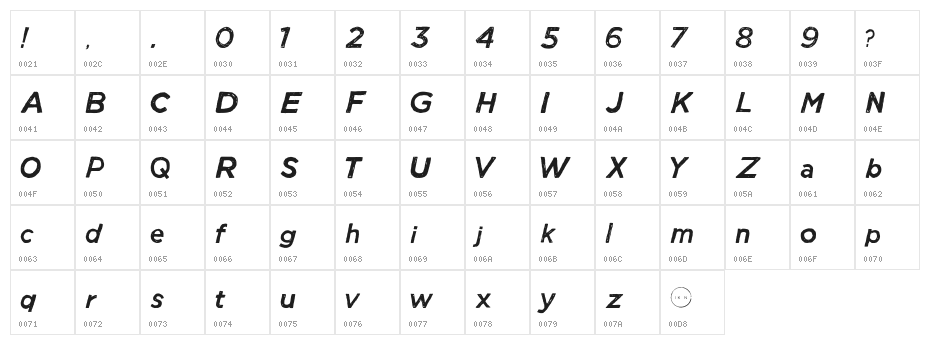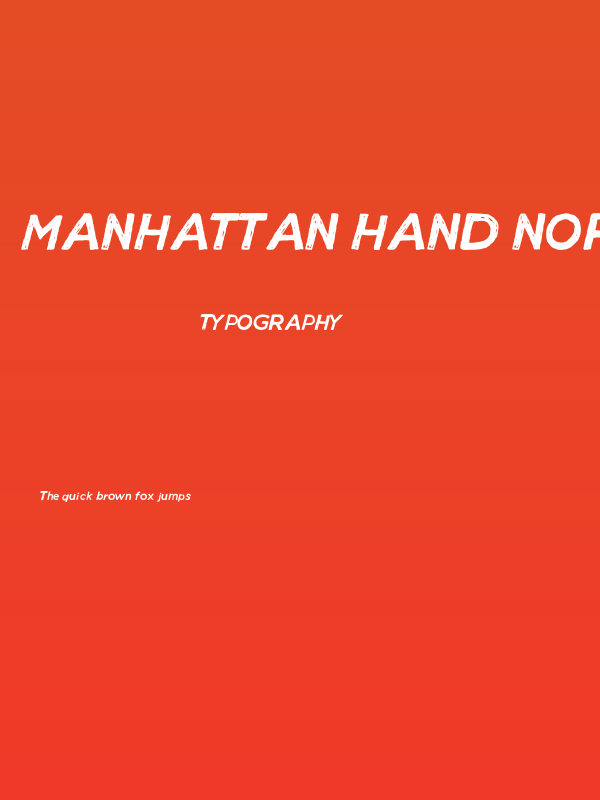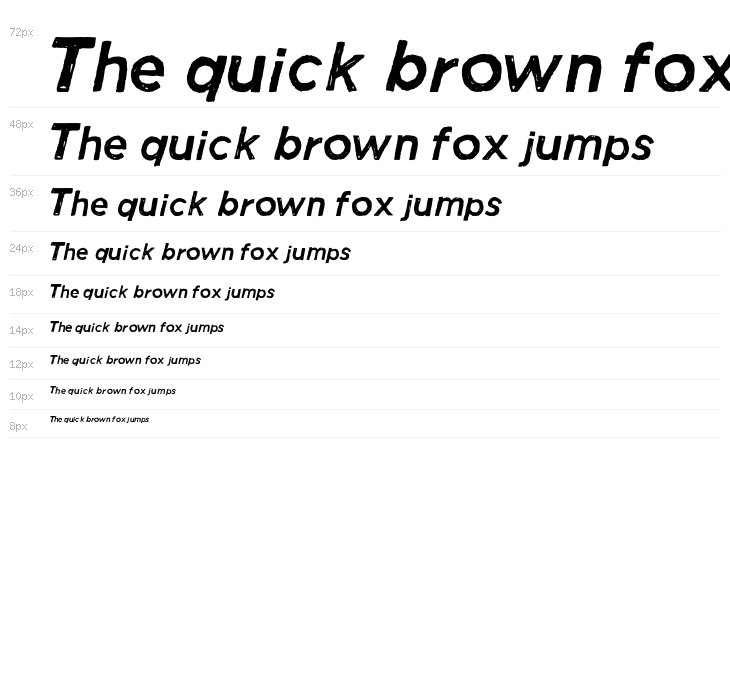
Manhattan Hand Normal Italic Font
✎ Distorted Eroded
| Caso d'uso | Headlines, Logos, Creative projects |
| Progetti proposti | Ideal for creative projects such as greeting cards, invitations, posters, and branding materials that require a personal and artistic touch. |